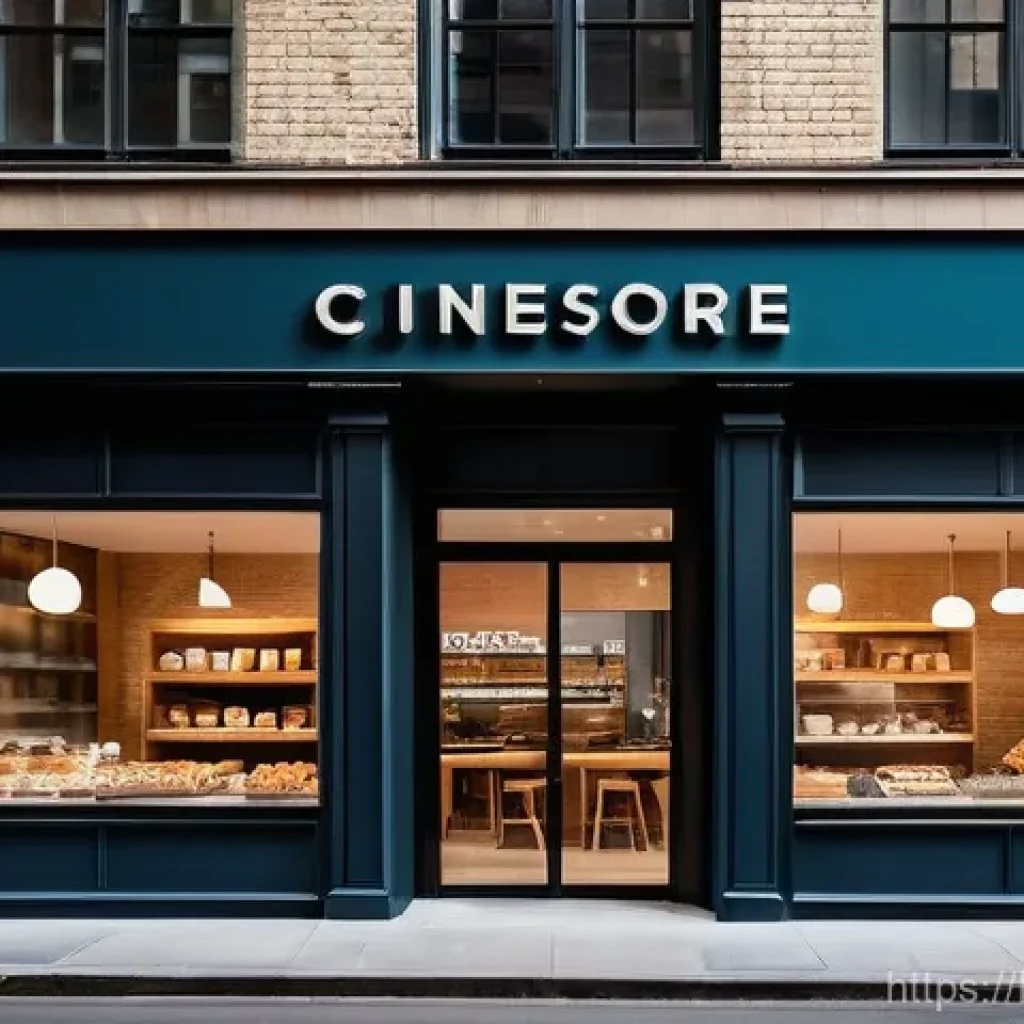
फ़ॉन्ट की शक्ति: आपके दस्तावेज़ डिज़ाइन को नया जीवन देने के 7 तरीके
नमस्ते मेरे प्यारे रीडर्स! क्या कभी आपने सोचा है कि सिर्फ एक छोटे से फॉन्ट को बदल देने से किसी डॉक्यूमेंट या वेबसाइट की पूरी जान कैसे बदल सकती है? मैंने खुद अपने अनुभव से महसूस किया है कि फॉन्ट सिर्फ अक्षर नहीं होते, ये हमारी भावनाएं, हमारा संदेश और हमारी ब्रांड की पहचान होते हैं.
आजकल की इस डिजिटल दुनिया में जहां हर कोई अपनी बात सबसे अलग तरीके से रखना चाहता है, वहां सही फॉन्ट चुनना किसी कला से कम नहीं है. मुझे याद है, एक बार मैंने अपने एक ब्लॉग पोस्ट के लिए गलत फॉन्ट चुन लिया था, और यकीन मानिए, मेरे पाठक उस पोस्ट से बिल्कुल भी कनेक्ट नहीं कर पा रहे थे.
जैसे ही मैंने फॉन्ट बदला, जादू हो गया! लोगों के कमेंट्स और जुड़ाव में जबरदस्त उछाल आया. ये सिर्फ खूबसूरती की बात नहीं है, बल्कि यह इस बात से जुड़ा है कि आपके पाठक आपके कंटेंट को कितनी आसानी से पढ़ और समझ पाते हैं.
2025 और उसके बाद भी, डिजाइन की दुनिया में फॉन्ट के नए-नए ट्रेंड्स (जैसे वेरिएबल फॉन्ट्स, नियो-विंटेज स्टाइल्स और AI-जनरेटेड टाइपफेस) आने वाले हैं जो क्रिएटिविटी को एक नया आयाम देंगे.
अब फॉन्ट सिर्फ स्टाइलिश दिखना ही नहीं, बल्कि यूजर एक्सपीरियंस को बेहतर बनाना और आपके ब्रांड की कहानी को सही ढंग से कहना भी उनका काम है. तो अगर आप भी चाहते हैं कि आपका कंटेंट सिर्फ पढ़ा न जाए, बल्कि महसूस भी किया जाए और लोगों के दिलों पर अपनी छाप छोड़े, तो फॉन्ट की इस जादुई दुनिया को समझना बेहद ज़रूरी है.
चाहे आप एक ब्लॉगर हों, ग्राफिक डिजाइनर हों या अपने बिज़नेस के लिए कोई प्रेजेंटेशन बना रहे हों, सही फॉन्ट का चुनाव आपकी सफलता की कुंजी बन सकता है. नीचे दिए गए लेख में हम फॉन्ट के इस गहरे प्रभाव और इसे अपने फायदे के लिए कैसे इस्तेमाल करें, इस पर विस्तार से जानेंगे!
फ़ॉन्ट सिर्फ़ अक्षर नहीं, आपकी ब्रांड की आवाज़ हैं!
अरे मेरे प्यारे दोस्तों, क्या आप जानते हैं कि एक छोटा सा फॉन्ट भी आपके पूरे ब्रांड की पहचान को बदल सकता है? मैंने खुद अपने कई सालों के अनुभव से सीखा है कि फॉन्ट सिर्फ अक्षर नहीं होते, ये आपकी कंपनी की पर्सनालिटी, आपके संदेश और आपकी कहानी को कहने का एक दमदार तरीका होते हैं. जब मैंने पहली बार एक छोटे स्टार्टअप के लिए वेबसाइट डिजाइन की थी, तो मैंने बस ऐसे ही एक “अच्छा दिखने वाला” फॉन्ट चुन लिया था. लेकिन कुछ ही समय बाद मुझे एहसास हुआ कि वो फॉन्ट मेरे ब्रांड के मूल्यों को बिल्कुल भी नहीं दर्शा रहा था. मेरे क्लाइंट्स को भी कुछ अजीब सा लग रहा था, जैसे कुछ कमी है. फिर मैंने थोड़ा रिसर्च किया और अपने ब्रांड की थीम के हिसाब से एक नया, मजबूत और विश्वसनीय फॉन्ट चुना. यकीन मानिए, बस इतना करने भर से मेरे ब्रांड की पूरी इमेज ही बदल गई! लोगों को अब मेरा काम ज़्यादा पेशेवर और विश्वसनीय लगने लगा. यह मेरे लिए एक आँखें खोलने वाला अनुभव था, जिसने मुझे सिखाया कि फॉन्ट का चुनाव कितना अहम होता है.
आपके ब्रांड की पहचान कैसे बताता है फ़ॉन्ट?
जब आप कोई वेबसाइट खोलते हैं या कोई विज्ञापन देखते हैं, तो सबसे पहले आप क्या नोटिस करते हैं? रंग और तस्वीरें, है ना? लेकिन इसके ठीक बाद जो चीज़ आपके दिमाग में सबसे ज़्यादा असर डालती है, वह है टेक्स्ट का फ़ॉन्ट. एक बोल्ड, आधुनिक सेंस-सेरिफ़ फ़ॉन्ट एक युवा, गतिशील ब्रांड की बात करेगा, जबकि एक क्लासिक, एलिगेंट सेरिफ़ फ़ॉन्ट किसी लग्ज़री या पारंपरिक ब्रांड की कहानी सुनाएगा. मैंने कई बार देखा है कि लोग अपने ब्रांड के लिए लाखों रुपये खर्च करते हैं लोगो और मार्केटिंग पर, लेकिन फ़ॉन्ट को बस यूं ही छोड़ देते हैं. यह एक बहुत बड़ी गलती है! आपका फ़ॉन्ट आपके ब्रांड का एक गैर-मौखिक संदेशवाहक है, जो आपके ग्राहकों को आपके बारे में बहुत कुछ बताता है, बिना एक शब्द बोले. मेरा मानना है कि फ़ॉन्ट का चुनाव आपके ब्रांड की नींव रखने जैसा है – अगर नींव मज़बूत नहीं होगी, तो इमारत कैसे टिकेगी?
भावनाओं को व्यक्त करने का ज़रिया
क्या आपने कभी सोचा है कि कुछ फ़ॉन्ट आपको खुशी देते हैं, कुछ आपको गंभीर महसूस कराते हैं, और कुछ आपको आराम देते हैं? यह कोई संयोग नहीं है! फ़ॉन्ट में भावनाओं को व्यक्त करने की एक अद्भुत शक्ति होती है. एक हस्तलिखित (script) फ़ॉन्ट आपको किसी दोस्त के लिखे पत्र की याद दिला सकता है, जिससे अपनत्व का भाव आता है. वहीं, एक बहुत ही सीधा और ज्यामितीय (geometric) फ़ॉन्ट आपको एक तकनीकी या वैज्ञानिक कॉन्टेंट की याद दिलाएगा, जिससे सटीकता का एहसास होता है. मुझे याद है, एक बार मैंने एक ब्लॉग पोस्ट लिखा था जिसका विषय बहुत ही भावनात्मक था – जीवन में चुनौतियों से कैसे निपटें. मैंने शुरुआत में एक सामान्य फ़ॉन्ट का इस्तेमाल किया, लेकिन मुझे लगा कि कुछ कमी है. फिर मैंने एक ऐसा फ़ॉन्ट चुना जिसमें थोड़ी गर्माहट और सहजता थी. पाठकों ने बताया कि उन्हें लगा जैसे मैं व्यक्तिगत रूप से उनसे बात कर रहा था! यह अनुभव बताता है कि सही फ़ॉन्ट आपके शब्दों में जान डाल सकता है और पाठकों के साथ गहरा भावनात्मक रिश्ता बना सकता है.
सही फ़ॉन्ट का चुनाव: पाठकों के दिल तक पहुँचने का सीधा रास्ता
दोस्तों, हम सब चाहते हैं कि हमारा कॉन्टेंट सिर्फ पढ़ा न जाए, बल्कि उसे समझा भी जाए और उसे याद रखा जाए. लेकिन क्या आपको पता है कि यह काम कितना आसान हो जाता है अगर आप सही फॉन्ट चुनें? मैंने खुद यह महसूस किया है कि अगर फॉन्ट पढ़ने में मुश्किल हो, तो पाठक एक-दो लाइन पढ़कर ही बोर हो जाते हैं और पेज छोड़ देते हैं. यह ऐसा है जैसे आपने किसी बहुत अच्छी कहानी को बहुत ही खराब आवाज़ में सुनाया हो – कोई सुनना ही नहीं चाहेगा! मेरे एक दोस्त ने एक बार अपनी ऑनलाइन दुकान खोली थी, और उसने अपने प्रोडक्ट डिस्क्रिप्शन के लिए एक बहुत ही फैंसी लेकिन अजीब सा फॉन्ट चुना था. वह सोचता था कि यह ‘अलग’ दिखेगा, लेकिन सच्चाई यह थी कि लोग उसके डिस्क्रिप्शन को पढ़ ही नहीं पा रहे थे. बिक्री घट रही थी. जब मैंने उसे सलाह दी कि वह एक सादा और स्पष्ट फॉन्ट इस्तेमाल करे, तो उसकी बिक्री में एकदम से उछाल आया. लोग अब उसके उत्पादों को समझ पा रहे थे. तो देखा आपने, सही फॉन्ट का चुनाव केवल सौंदर्यशास्त्र का मामला नहीं है, यह सीधा आपके पाठकों या ग्राहकों के अनुभव और आपके व्यापार की सफलता से जुड़ा है.
पढ़ने में आसानी और आँखों का आराम
आप कितने भी अच्छे लेखक क्यों न हों, अगर आपका टेक्स्ट पढ़ने में मुश्किल है, तो पाठक उसे छोड़ देंगे. यह एक कड़वा सच है. सही फॉन्ट वो होता है जो आपकी आँखों को थकाता नहीं है, चाहे आप कितना भी लंबा टेक्स्ट पढ़ें. मेरे ब्लॉग पर मैं हमेशा ऐसे फॉन्ट का इस्तेमाल करता हूँ जो विभिन्न स्क्रीन साइज़ पर भी स्पष्ट दिखें और आँखों पर ज़ोर न डालें. खासकर जब हम मोबाइल पर पढ़ते हैं, तो छोटे अक्षर और अस्पष्ट फॉन्ट बहुत परेशान करते हैं. सेंस-सेरिफ़ फ़ॉन्ट जैसे ‘ओपन सेंस’ या ‘रोबोटो’ आमतौर पर स्क्रीन पर बहुत अच्छे लगते हैं क्योंकि वे साफ़ और सीधे होते हैं. सेरिफ़ फ़ॉन्ट जैसे ‘जॉर्जिया’ या ‘लोरा’ प्रिंट के लिए बहुत अच्छे माने जाते हैं, क्योंकि उनके छोटे स्ट्रोक अक्षर को जोड़ने में मदद करते हैं. एक अच्छा फ़ॉन्ट चुनना ऐसा है जैसे आप अपने पाठकों के लिए एक आरामदायक कुर्सी और अच्छी रोशनी का इंतज़ाम कर रहे हों – वे ज़्यादा देर तक रुकना चाहेंगे और आपकी बातों को ध्यान से सुनेंगे.
लक्षित दर्शकों के अनुसार चुनाव
आप किसके लिए लिख रहे हैं? क्या आप युवाओं के लिए लिख रहे हैं, या वरिष्ठ नागरिकों के लिए? क्या आप एक तकनीकी ब्लॉग चला रहे हैं, या एक फैशन ब्लॉग? आपके लक्षित दर्शक कौन हैं, यह जानना फॉन्ट चुनने में बहुत मददगार होता है. अगर आपका दर्शक वर्ग युवा है, तो आप थोड़े आधुनिक या ट्रेंडी फॉन्ट के साथ प्रयोग कर सकते हैं. लेकिन अगर आपके दर्शक थोड़े ज़्यादा उम्र वाले हैं, तो आपको सादे, बड़े और स्पष्ट फॉन्ट का चुनाव करना चाहिए ताकि उन्हें पढ़ने में आसानी हो. मैंने एक बार एक हेल्थ ब्लॉग के लिए काम किया था, जिसके पाठक ज़्यादातर मध्यम आयु वर्ग के लोग थे. हमने शुरुआत में एक बहुत पतला (thin) और स्टाइलिश फॉन्ट इस्तेमाल किया, लेकिन बाद में फ़ीडबैक आया कि लोगों को पढ़ने में दिक्कत हो रही थी. हमने तुरंत उसे एक मोटे और स्पष्ट फॉन्ट से बदला, और आप विश्वास नहीं करेंगे, पाठकों की संख्या और उनके कमेंट्स में तुरंत सुधार हुआ. यह हमें सिखाता है कि अपने दर्शकों को समझना और उनके हिसाब से चीज़ें बनाना कितना ज़रूरी है.
इन ट्रेंड्स को अपने कंटेंट में शामिल करने के लिए, आप हेडिंग्स में वेरिएबल फॉन्ट्स का प्रयोग कर सकते हैं ताकि वे अलग-अलग स्क्रीन साइज़ पर शानदार दिखें.
नियो-विंटेज फॉन्ट्स को आप अपने ब्रांड की पहचान के रूप में इस्तेमाल कर सकते हैं, खासकर अगर आपका कंटेंट किसी खास नॉस्टैल्जिक फीलिंग से जुड़ा हो. याद रखें, इन नए फॉन्ट्स का स्मार्ट तरीके से इस्तेमाल करने से आपका कंटेंट न केवल ताज़ा और आधुनिक दिखेगा, बल्कि पाठकों को एक अनोखा विज़ुअल अनुभव भी देगा, जिससे वे आपकी वेबसाइट पर ज़्यादा देर रुकेंगे और बार-टार आएंगे – जो AdSense की कमाई के लिए सोने पे सुहागा है!